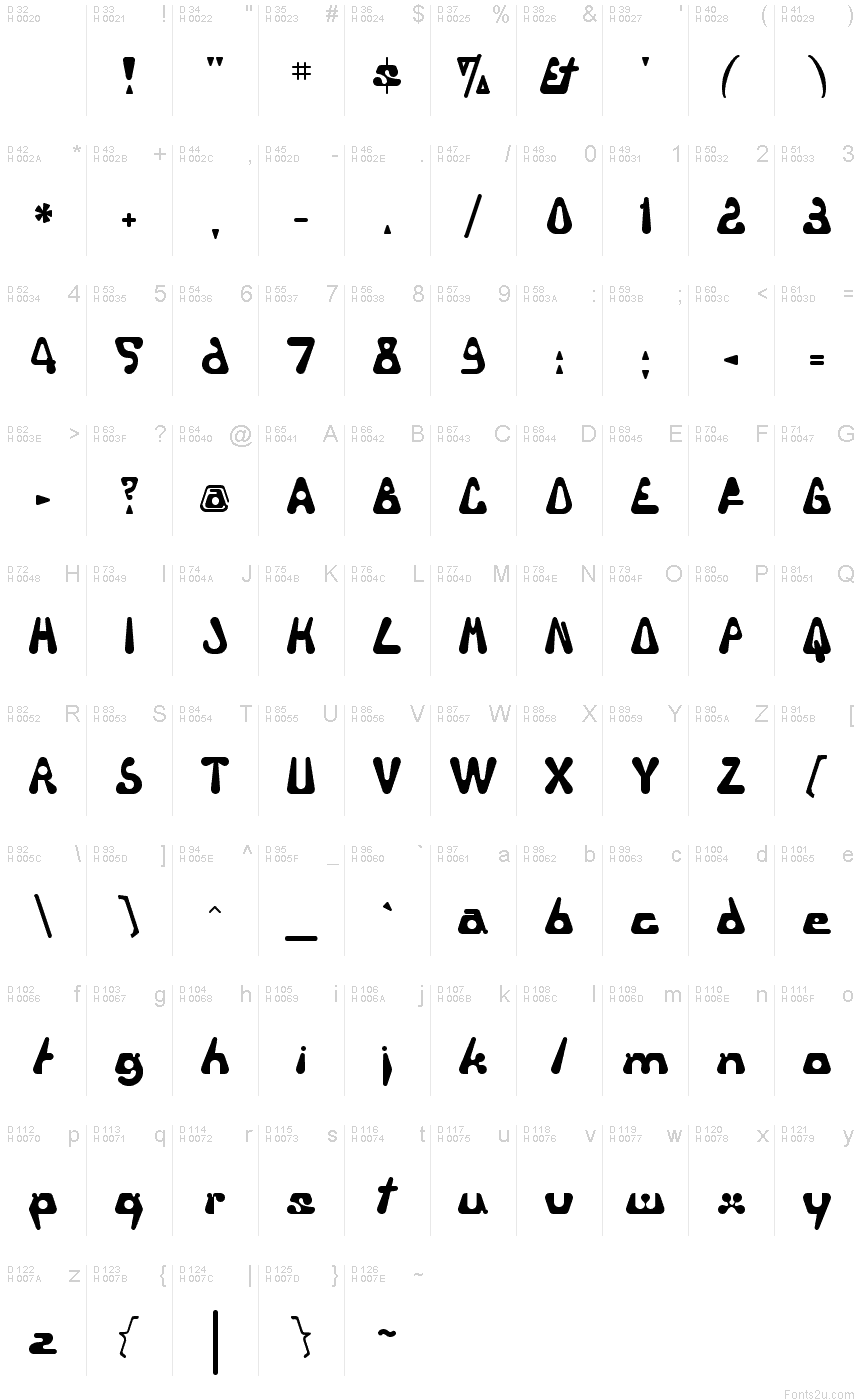
Triangulor
Triangulor autorstwa Jasona Pagury to darmowy, psychodeliczny krój displayowy z miękkimi, napuchniętymi literami, które sprawiają wrażenie odlanych, a nie narysowanych. Kształty opierają się na zaokrąglonych klinach, kroplowych łączeniach i małych, ostrych cięciach, które nadają czcionce zabawny i nieco dziwaczny charakter, przywołując klimat plakatów z przełomu lat 60. i 70., unikając przy tym przeładowania.
Najlepiej sprawdza się wszędzie tam, gdzie liternictwo staje się częścią obrazu: ulotki muzyczne, plakaty festiwalowe, okładki zinów, opakowania i plansze tytułowe. Jej swobodny, „trippowy” styl pasuje do projektów szukających czegoś nieoczywistego. Masywne krzywe i nietypowe otwory czynią ją świetnym wyborem do krótkich nagłówków czy inicjałów w stylu monogramów, gdzie te bulwiaste sylwetki robią największe wrażenie.